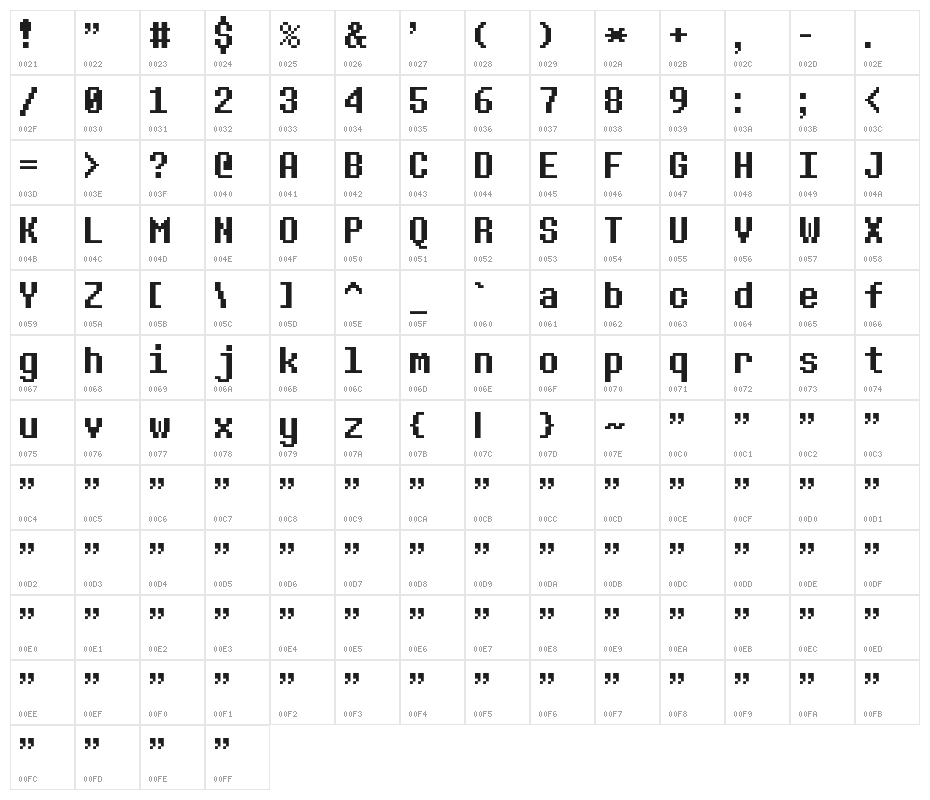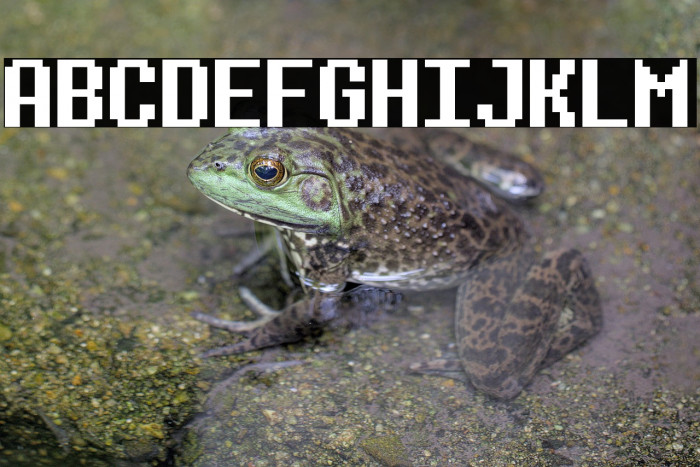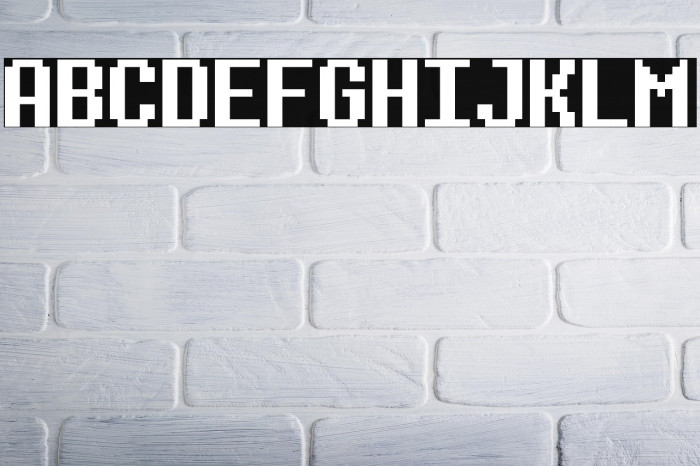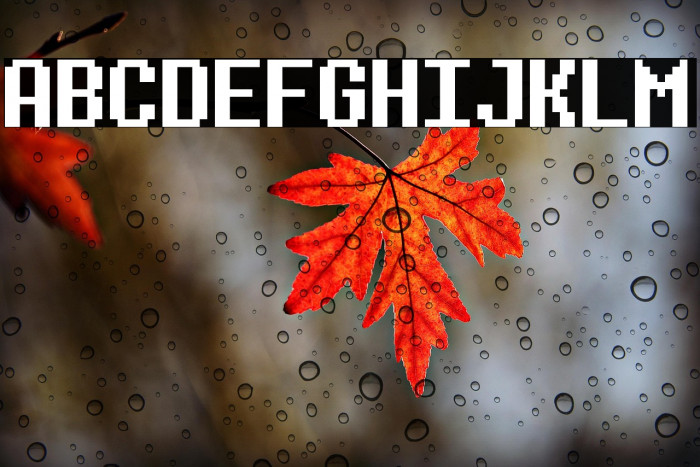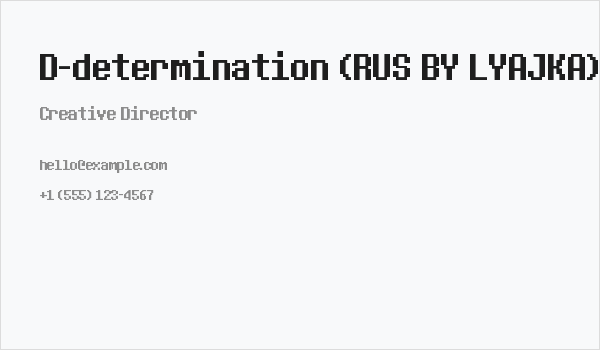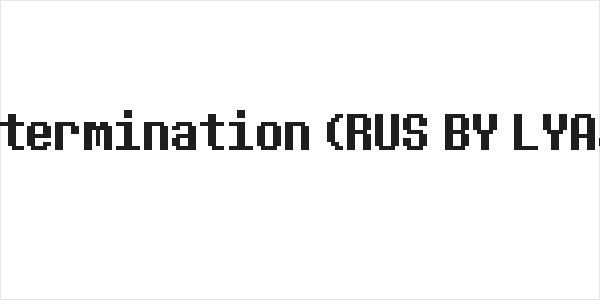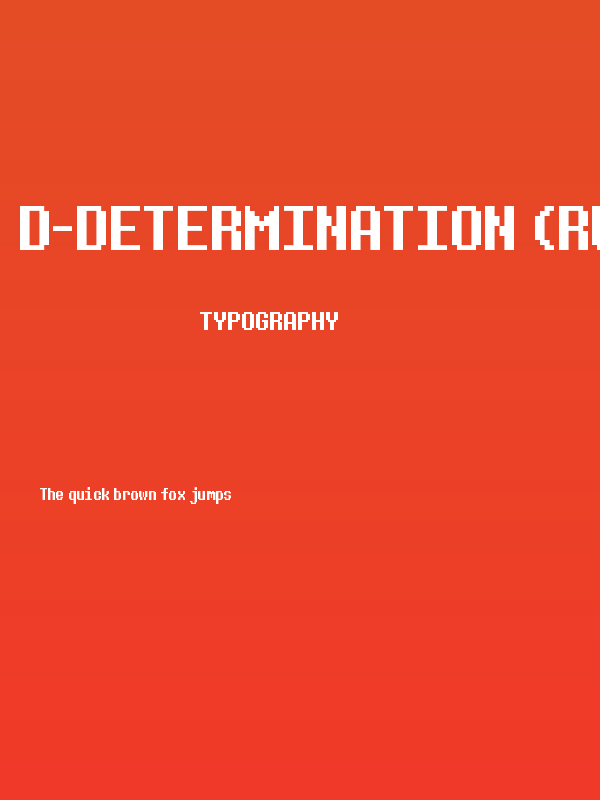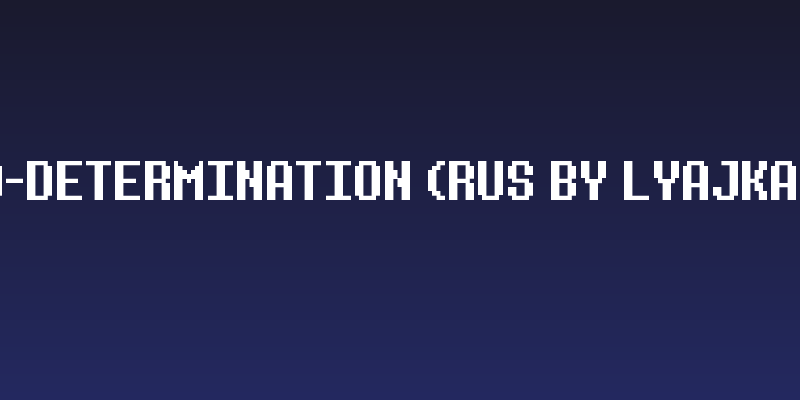
D-determination (RUS BY LYAJKA) Font
| Gesamtstil | Retro, Digital |
| Anwendungsfall | Headlines, Logos, Digital Art |
| Vorgeschlagene Projekte | Ideal for retro-themed designs, video game graphics, digital art projects, and any creative work that requires a nostalgic, pixelated look. |
D-determination (RUS BY LYAJKA)